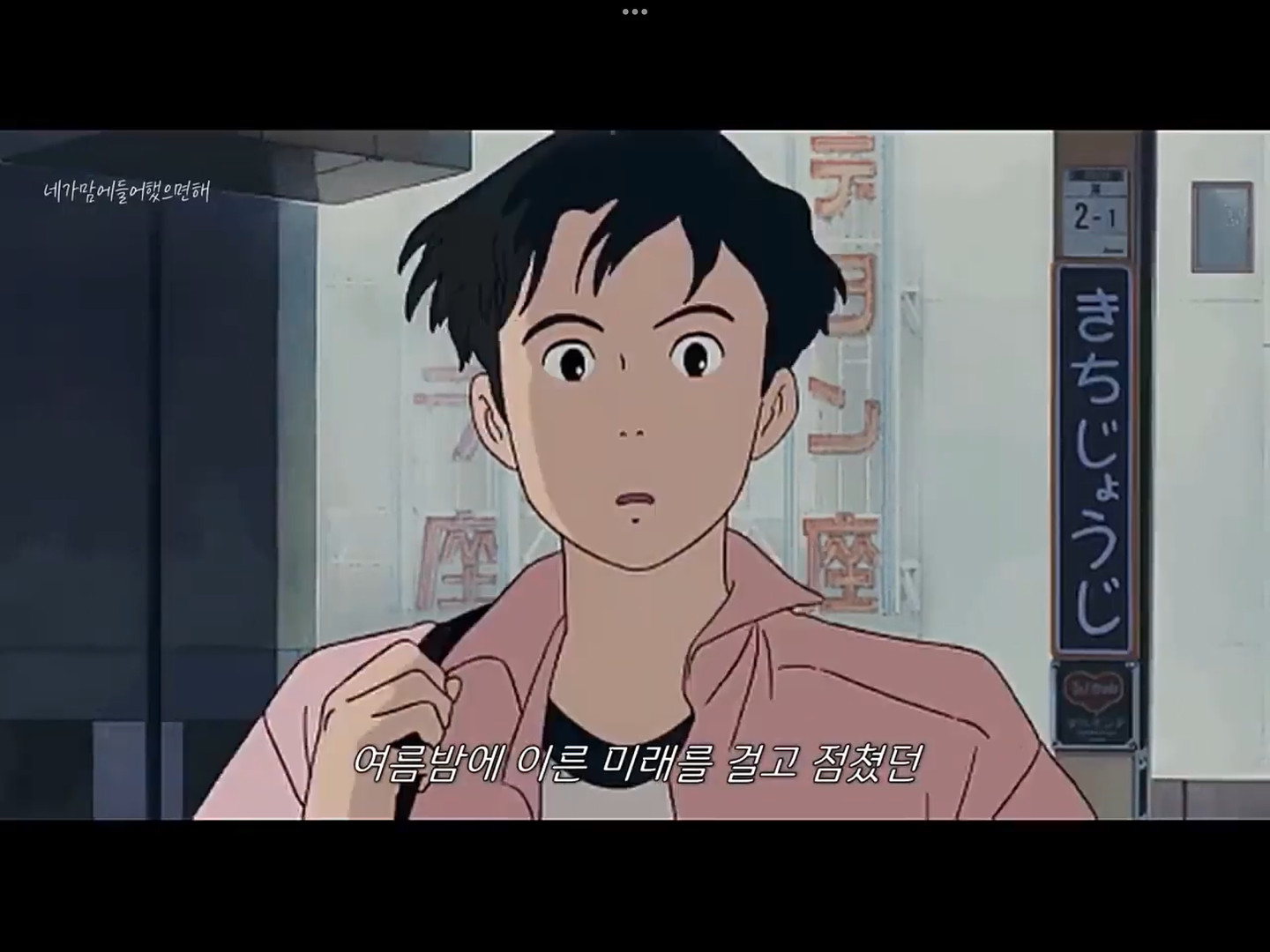
네가맘에들어했으면해 유튜브 자막입니다! 받침 ㄴ과 ㄹ의 끝이 위를 향해 굽어 있고, 초성 ㄷ, ㄹ, ㅁ이 한 번씩 끊겨있어요
한국만화영상진흥원 X 윤디자인
만화진흥원체 입니다.
네가맘에들어했으면해 유튜브 자막입니다! 받침 ㄴ과 ㄹ의 끝이 위를 향해 굽어 있고, 초성 ㄷ, ㄹ, ㅁ이 한 번씩 끊겨있어요